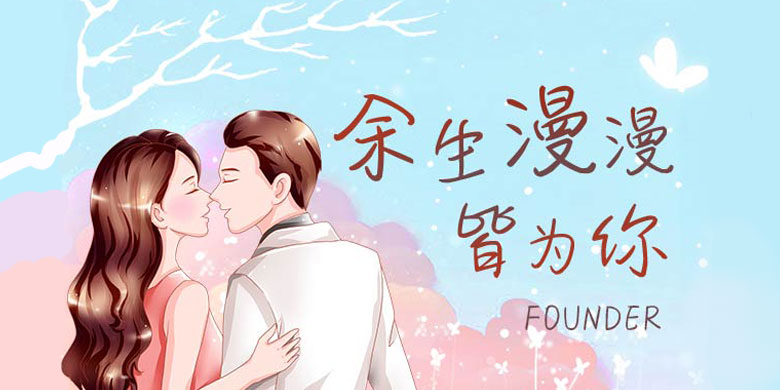
品牌:方正手迹设计师:尚正中发行时间:2020字库编码:大陆简体(GB2312-80)分类:创意书写字体属性:精品字
余生漫漫皆为你体,线条简约灵动,婉约流畅,笔势连绵映带,沉静悠远,书法气息浓厚。适用于文艺类的书刊、品牌广告和产品包装设计,现代诗歌、短文排版,影视字幕用字,以及社交网络的个性化用字。